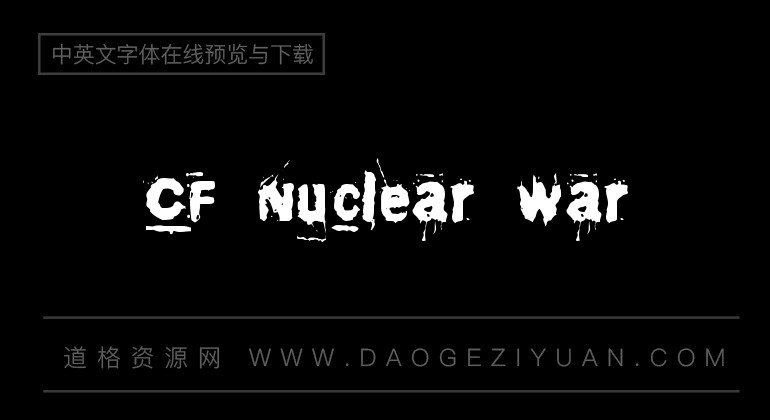
? CF Nuclear War 字体是一款拥有独特复古风格的英文字体,由 Creative Freedom 创作。它的特点是具有极强的冲击感,字体的形状有着明显的线条感,非常有视觉冲击力。它的字体设计也有利于增强文字的清晰度,使文字更加突出,更容易被读者所认知。除此之外,它还具有较强的复古风格,可以为您的设计带来更多的视觉效果。内容介绍
CF Nuclear War是一款非常不错的手写艺术字体,具有很好的视觉感,适合于文化类的宣传设计、商业类品牌的广告和产品包装设计以及个性化文字排版等较多场景。